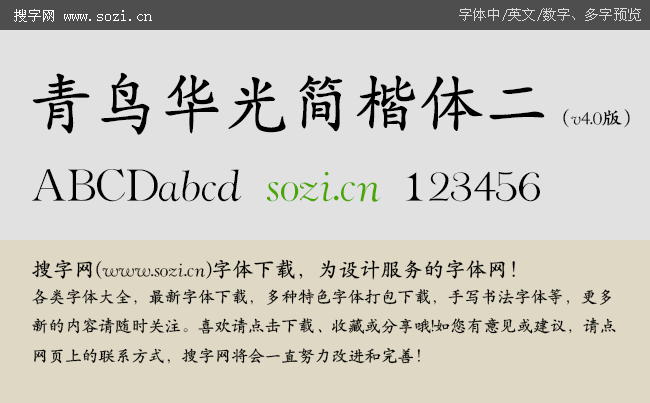
青鳥(niǎo)華光簡(jiǎn)楷體二
搜字網(wǎng)提供一款青鳥(niǎo)華光簡(jiǎn)楷體二中文字體下載,青鳥(niǎo)華光簡(jiǎn)楷體二字體方正,筆畫(huà)平直,,整體效果十分出色,適用于廣告設(shè)計(jì)、名片設(shè)計(jì)、包裝印刷、產(chǎn)品設(shè)計(jì)等應(yīng)用。